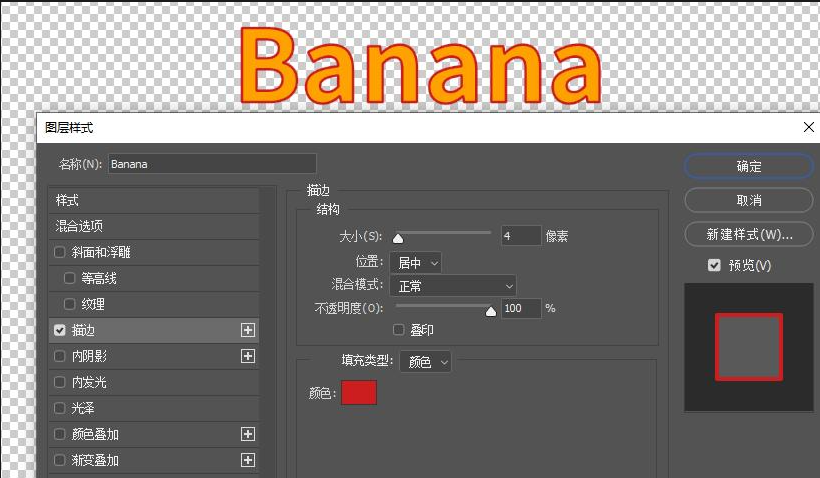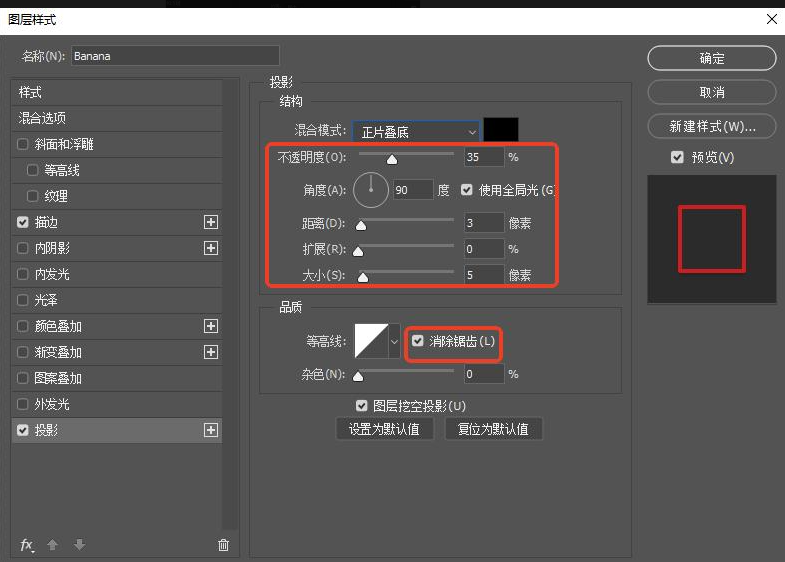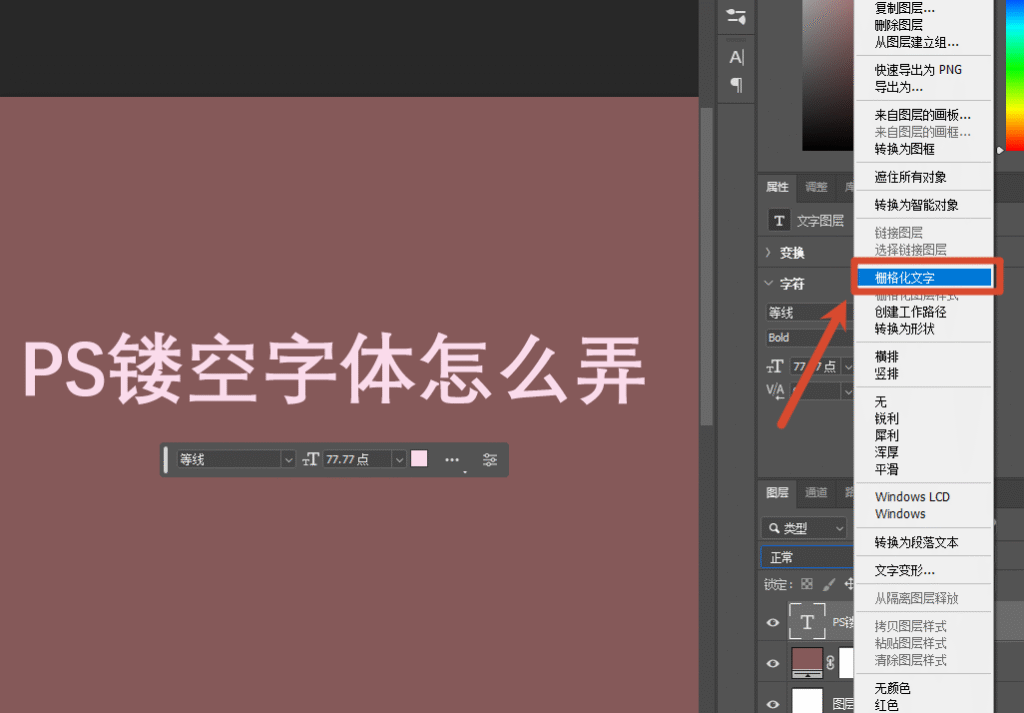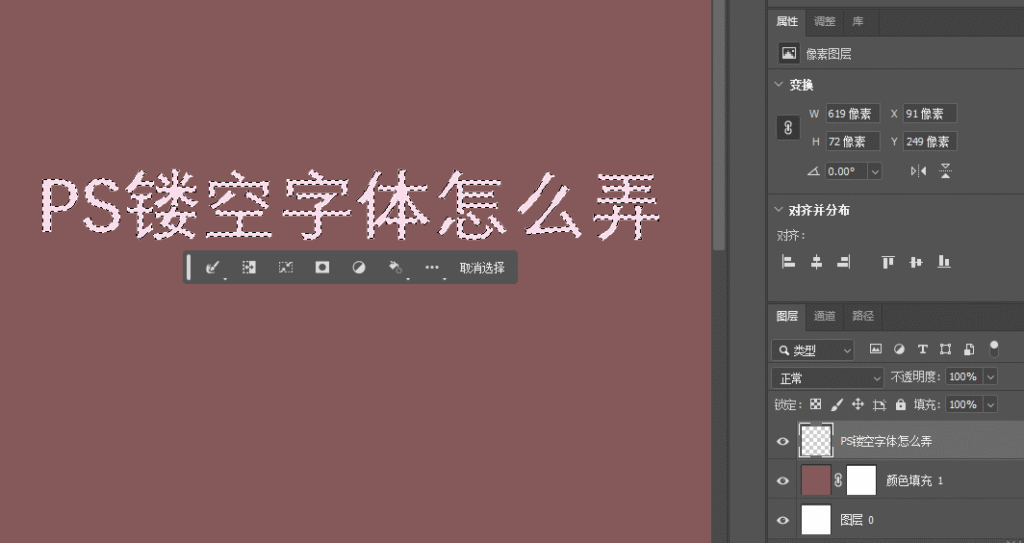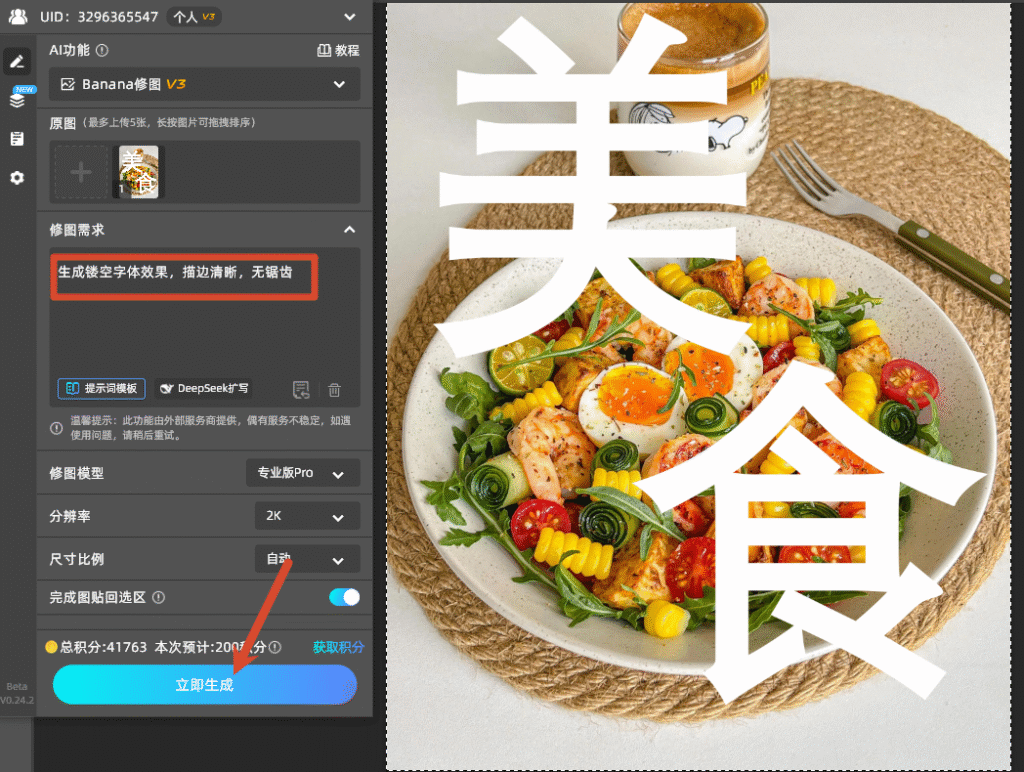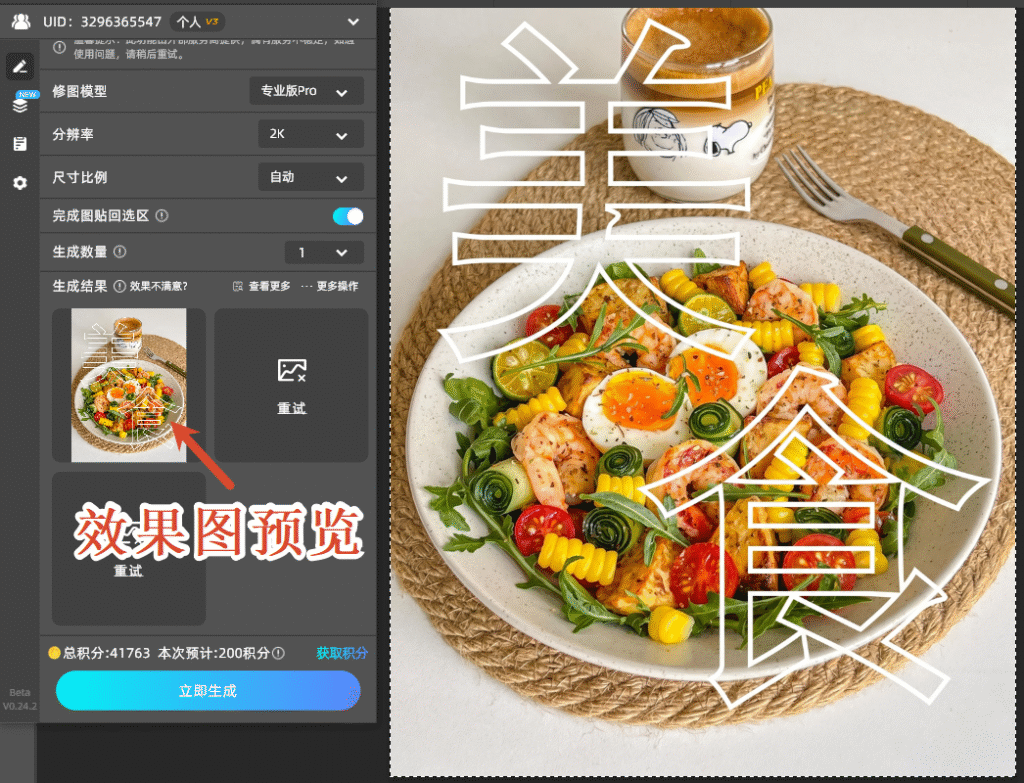
PS镂空字体怎么弄?3种零基础镂空字体制作方法
在平面设计、海报制作、LOGO 设计等场景中,镂空字体凭借简约通透的视觉效果,能快速提升作品高级感。很多新手想掌握 PS 镂空字体制作技巧,本文详细分享 PS 镂空字体制作的常用方法,包括基础操作与 AI 插件高效技巧,即使是零基础新手也能轻松学会。
一、PS 原生工具制作镂空字体(3 种基础方法)
(一)图层样式描边法(最简单,适合新手)
这是 PS 制作镂空字体最基础的方法,操作简单,能快速做出标准描边镂空效果,适合电商海报、宣传图等常规场景。
打开 PS,新建画布,选择横排文字工具(T),输入需要制作镂空效果的文字,设置字体(建议粗体,如 Impact、黑体)、字号(≥48pt,避免镂空后模糊)与颜色。
双击文字图层,打开图层样式面板,勾选描边选项,设置参数:大小 4-6px(字号越大描边可越粗)、位置 “居中”、颜色选与背景对比强烈的颜色。
描边
在图层样式面板中,将填充不透明度调为0%,此时文字内部完全透明,仅保留描边,形成镂空效果。
(可选增强)勾选 “投影”,距离设 3-5 像素,大小设 5 像素,让镂空文字更有立体感;勾选 “消除锯齿”,优化文字边缘顺滑度。
调整投影参数
(二)文字选区反向删除法(适合图片填充镂空)
该方法能让镂空区域透出下方图片,适合制作 “文字画框” 效果,常用于创意海报、封面设计。
导入背景图片,将其放在文字图层下方;选择文字图层,右键点击栅格化文字(文字转为像素图层,才能进行删除操作)。
栅格化文字
按住 Ctrl 键(Windows)或 Cmd 键(Mac),点击文字图层缩略图,载入文字轮廓选区。
载入文字轮廓选区
激活背景图片图层,按下 Shift+Ctrl+I(Windows)/Shift+Cmd+I(Mac) 反向选区,再按 Delete 键删除选区内像素,仅保留文字笔画区域的图片。
按 Ctrl+D 取消选区,即可看到图片从文字镂空区域透出的效果。
(一)StartAI 插件镂空字体制作步骤
输入文字:用文字工具输入内容,设置基础字体与字号,无需复杂调整。
一键生成:打开 StartAI 面板,选择Banana 修图功能,输入提示词 “生成镂空字体效果,描边清晰,无锯齿”,点击 “立即生成”,10-30 秒即可完成。
Banana修图
Banana修图效果图
二次调整:生成的镂空字体可直接在 PS 中修改描边粗细、颜色,或添加投影、内阴影等样式,适配不同设计场景。
三、PS 镂空字体制作实用小贴士
1. 字体选择:优先选择粗体、笔画规整的字体(如黑体、圆体、Impact),避免纤细字体,防止镂空后笔画断裂、模糊StartAI。
2. 描边参数:字号 48-72pt 时,描边大小设 4-6px;字号 100pt 以上时,描边大小设 8-12px,保证镂空效果清晰可见。
3. 背景搭配:深色背景搭配浅色描边、浅色背景搭配深色描边,增强镂空字体的视觉对比度,让效果更突出。
综上,PS 镂空字体制作可根据需求选择方法:新手入门用图层样式描边法,图片填充效果用选区反向删除法,复杂自定义效果用路径布尔运算法;追求高效与专业效果,直接用 StartAI 插件一键生成,零基础也能快速做出高质量镂空字体,助力设计创作高效落地。